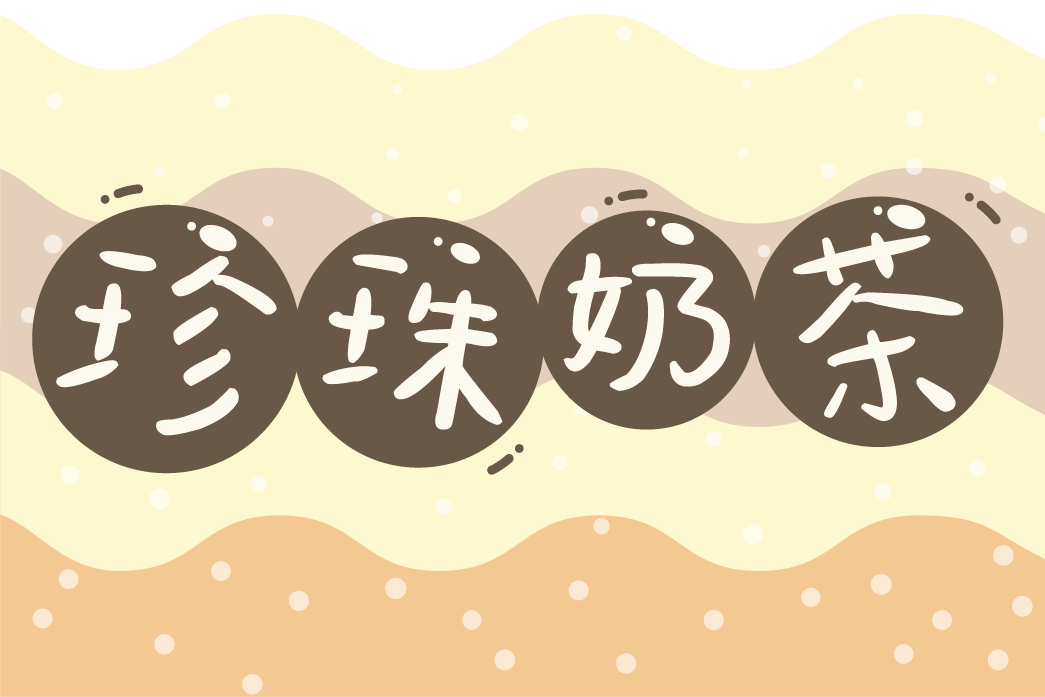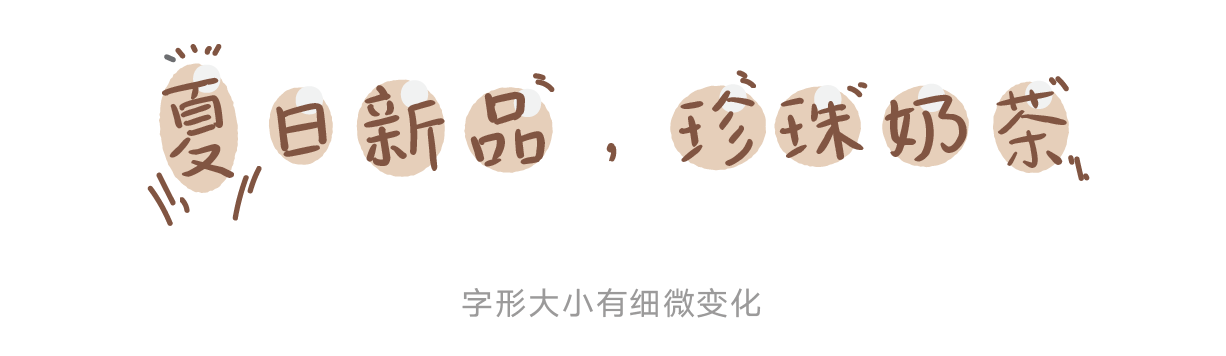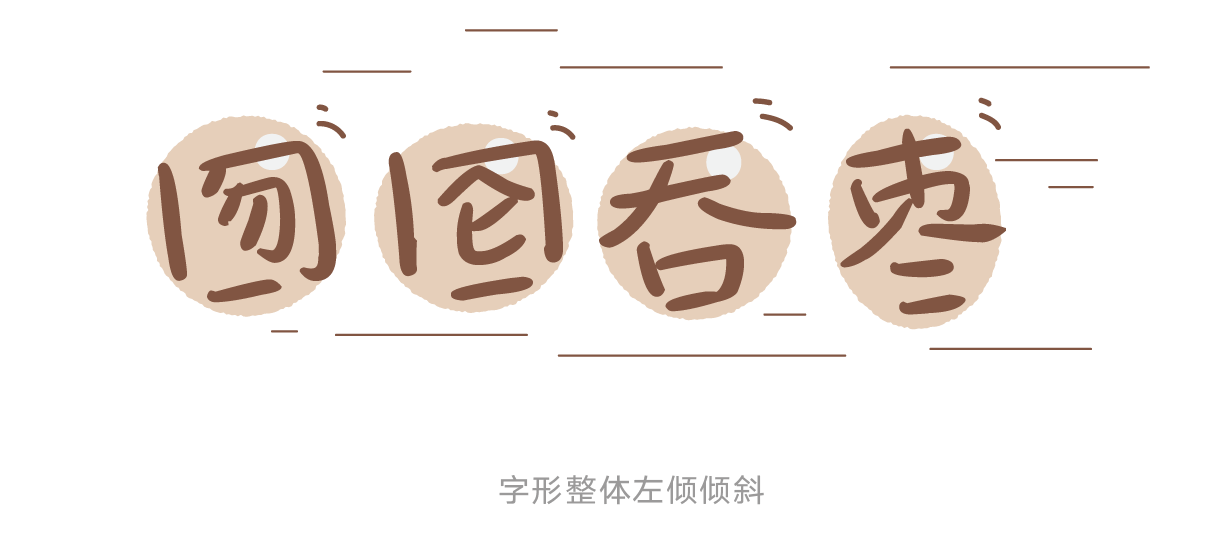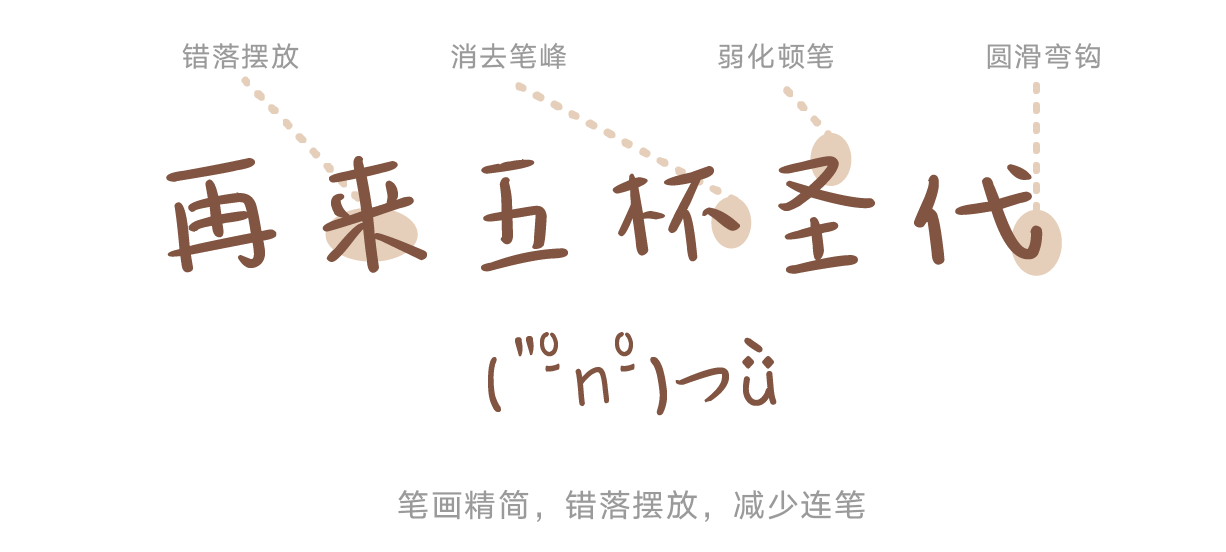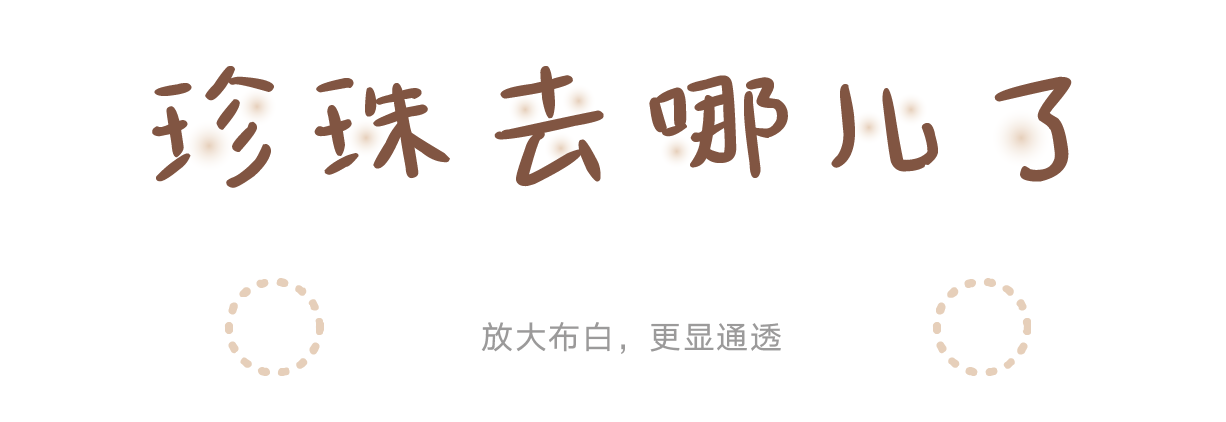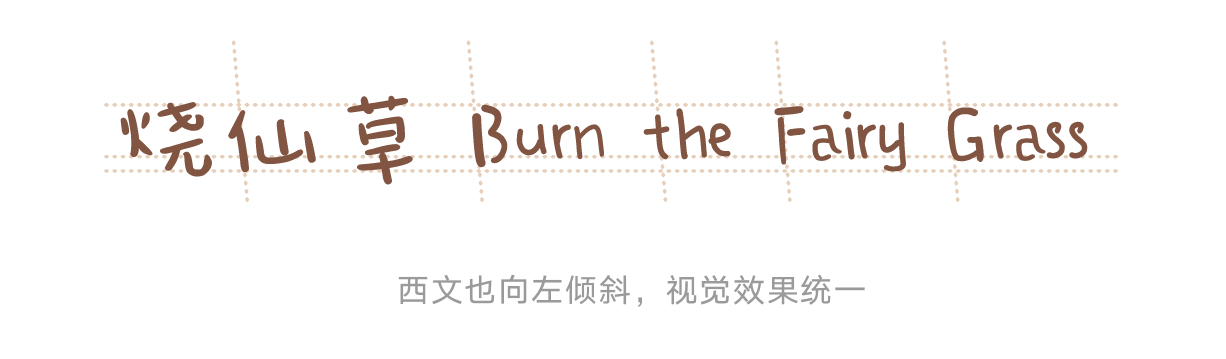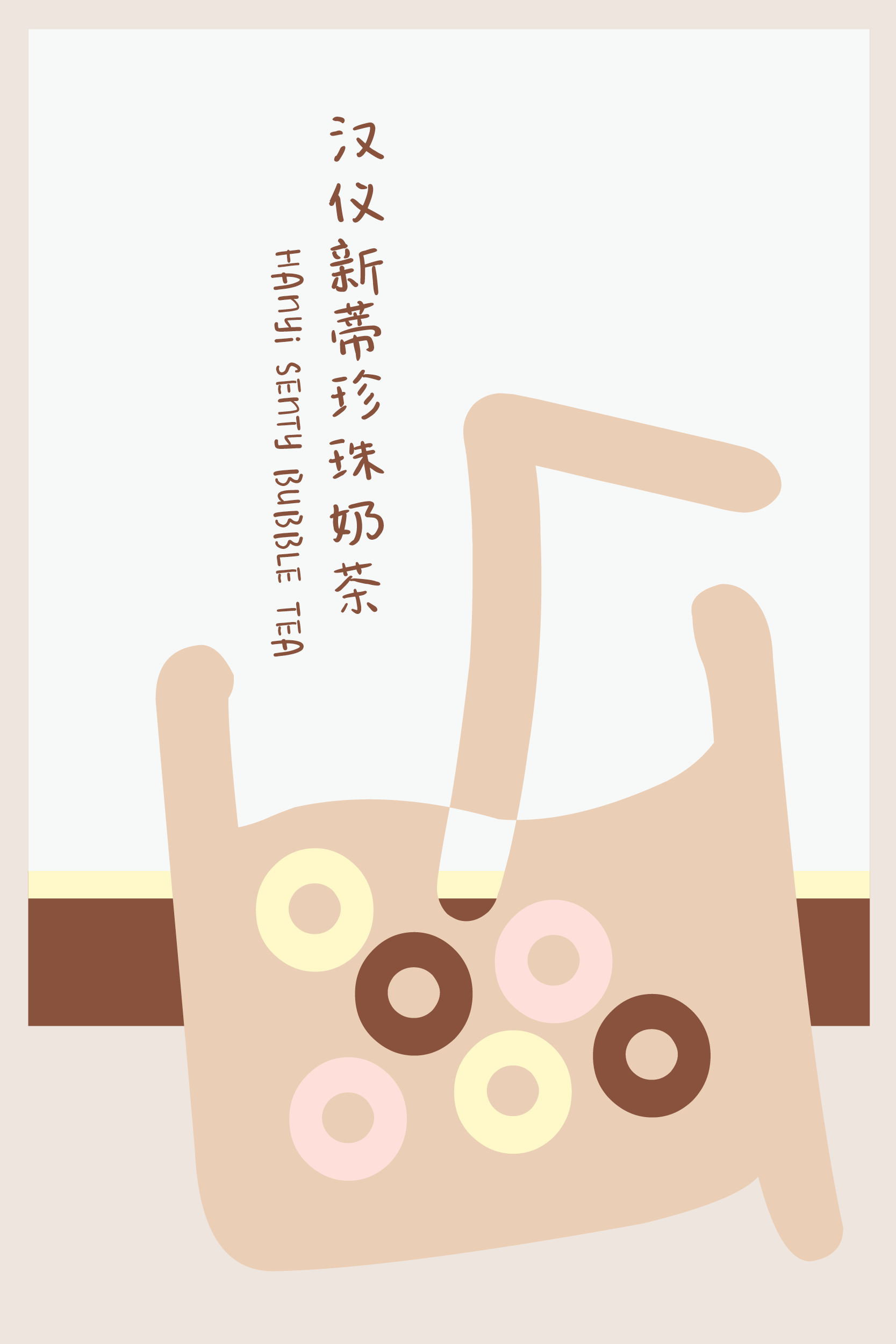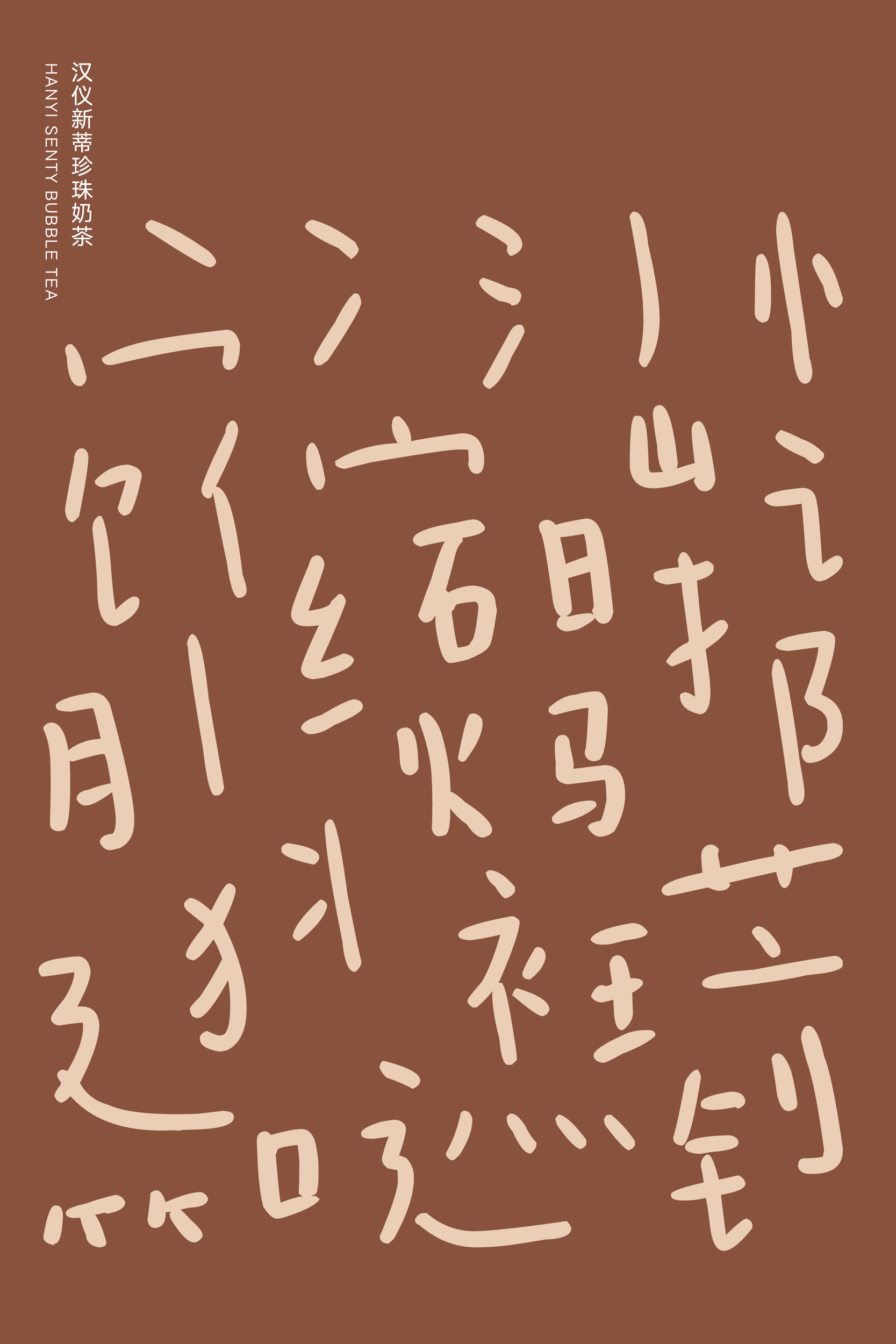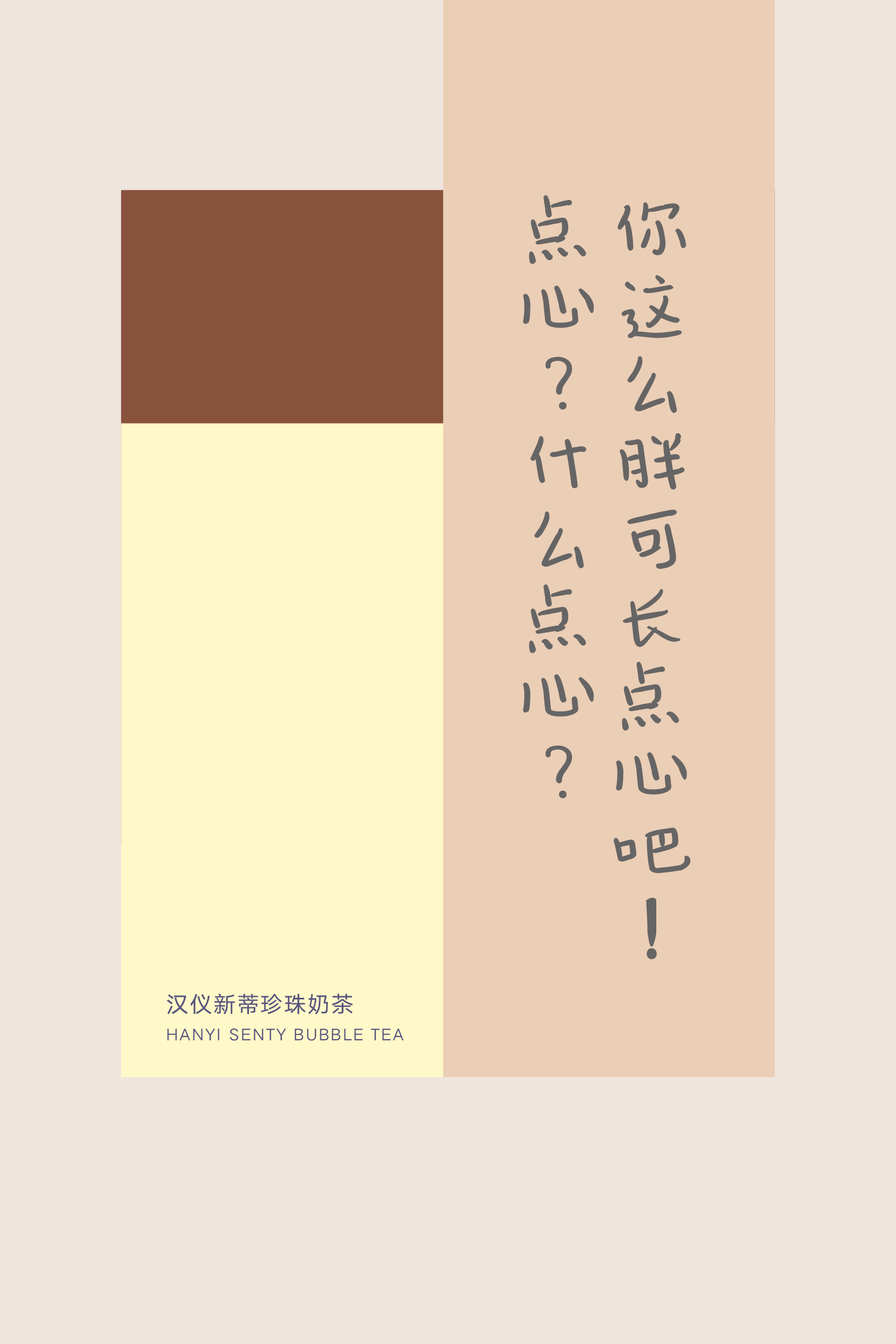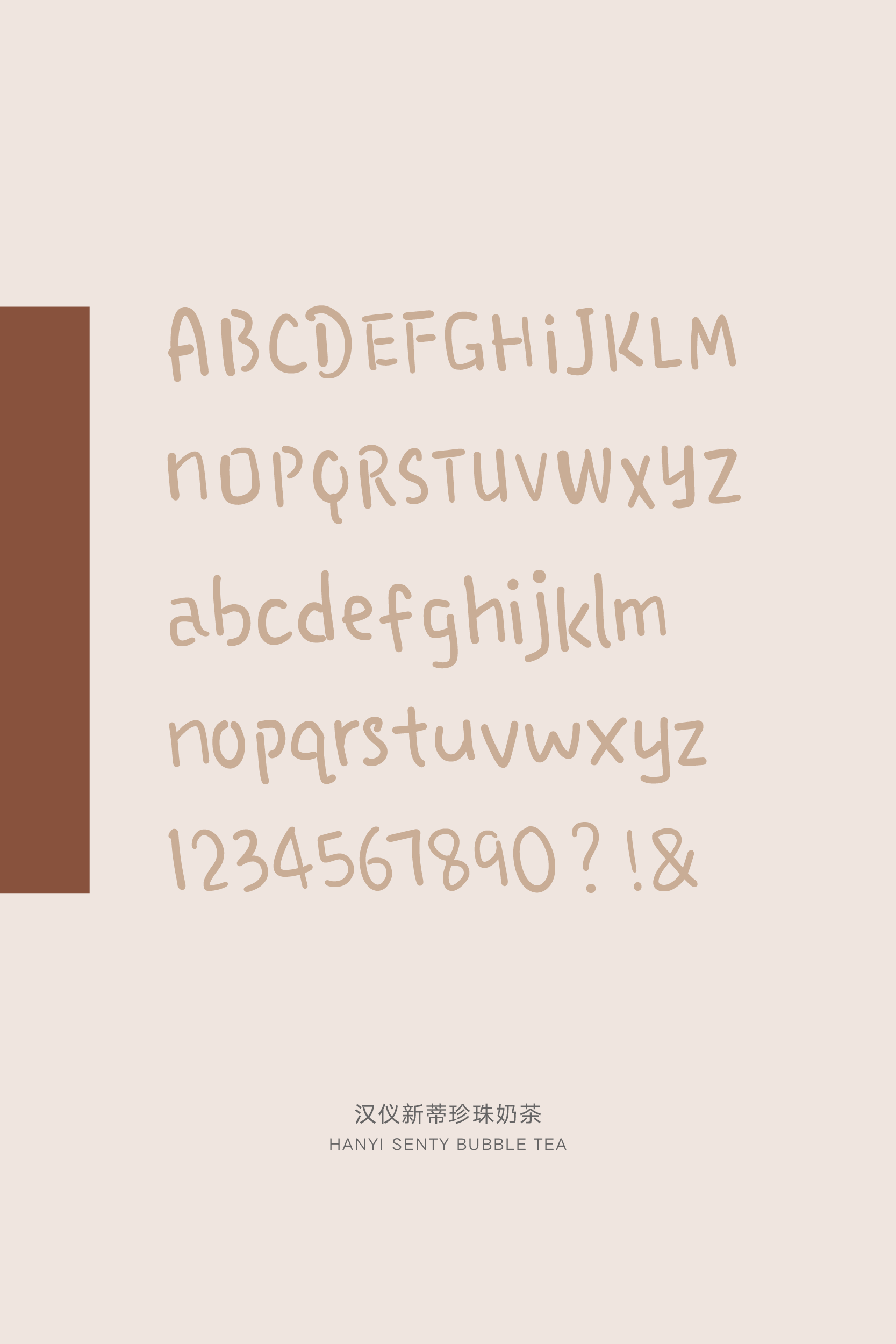
汉仪新蒂珍珠奶茶字体介绍,一款Q弹滑嫩、甜而不腻的手写字体
汉仪新蒂珍珠奶茶 | 字体简介
“汉仪新蒂珍珠奶茶”是一款Q弹滑嫩、甜而不腻的手写字体。字形圆润、通透,略微倾斜,带来元气与动感,给人珍珠奶茶般清新可爱的视觉感受。适用于产品包装、游戏动漫、广告综艺等短文案场合。
汉仪新蒂珍珠奶茶 | Q弹字形
“汉仪新蒂珍珠奶茶”字形整体圆润,不同字形有细微的大小变化,带来一种Q弹的跳跃感。
“汉仪新蒂珍珠奶茶”字形整体向左倾斜,一反目前主流字体向右倾斜的特征,就像散落在奶茶里的珍珠一样,摇摇晃晃,向后滚动。
汉仪新蒂珍珠奶茶 | 稚嫩笔画
“汉仪新蒂珍珠奶茶”的笔画错落摆放,道道精简、笔笔分明,减少书写连笔,使得字形看起来更加稚拙可爱,增添新鲜感。
“汉仪新蒂珍珠奶茶”放大了笔画的布白空间,增加了文字与段落的通透感。透过作者随性的笔画,整款字体在视觉上显得更加清新稚嫩。
汉仪新蒂珍珠奶茶|中西文匹配
“汉仪新蒂珍珠奶茶”的西文,笔画手写感十足,字形同样设计成了向后倾斜的样式,使得中西文视觉效果统一。
汉仪新蒂珍珠奶茶 | 字体样张
汉仪新蒂珍珠奶茶 | 彩蛋
“汉仪新蒂珍珠奶茶”运用了Opentype技术,在排版软件里,连续输入小写字母o,就能看到一杯杯珍珠奶茶被灌装的字体动画啦 !好看又好玩的字体,不来下载一个试试看吗?